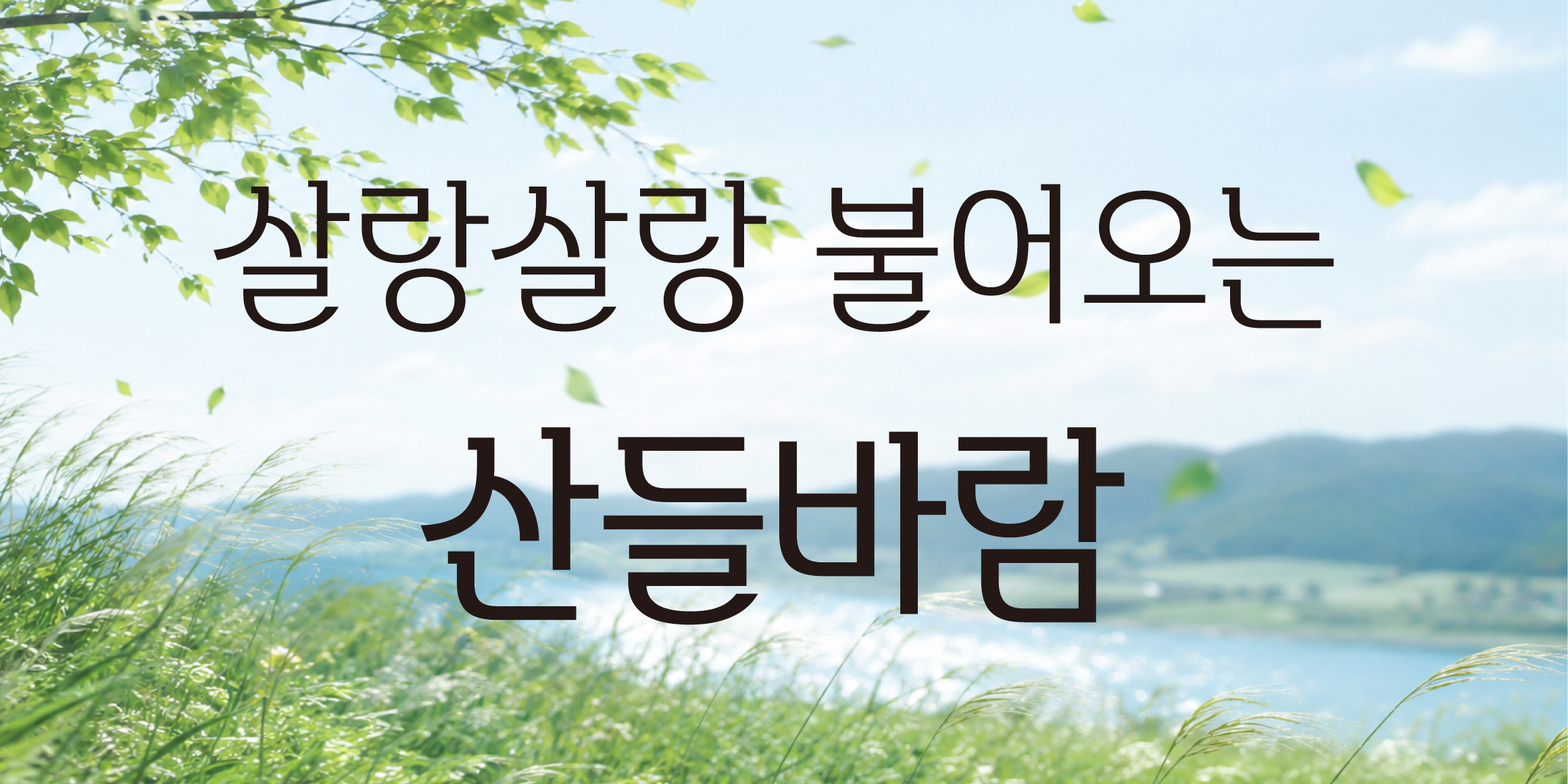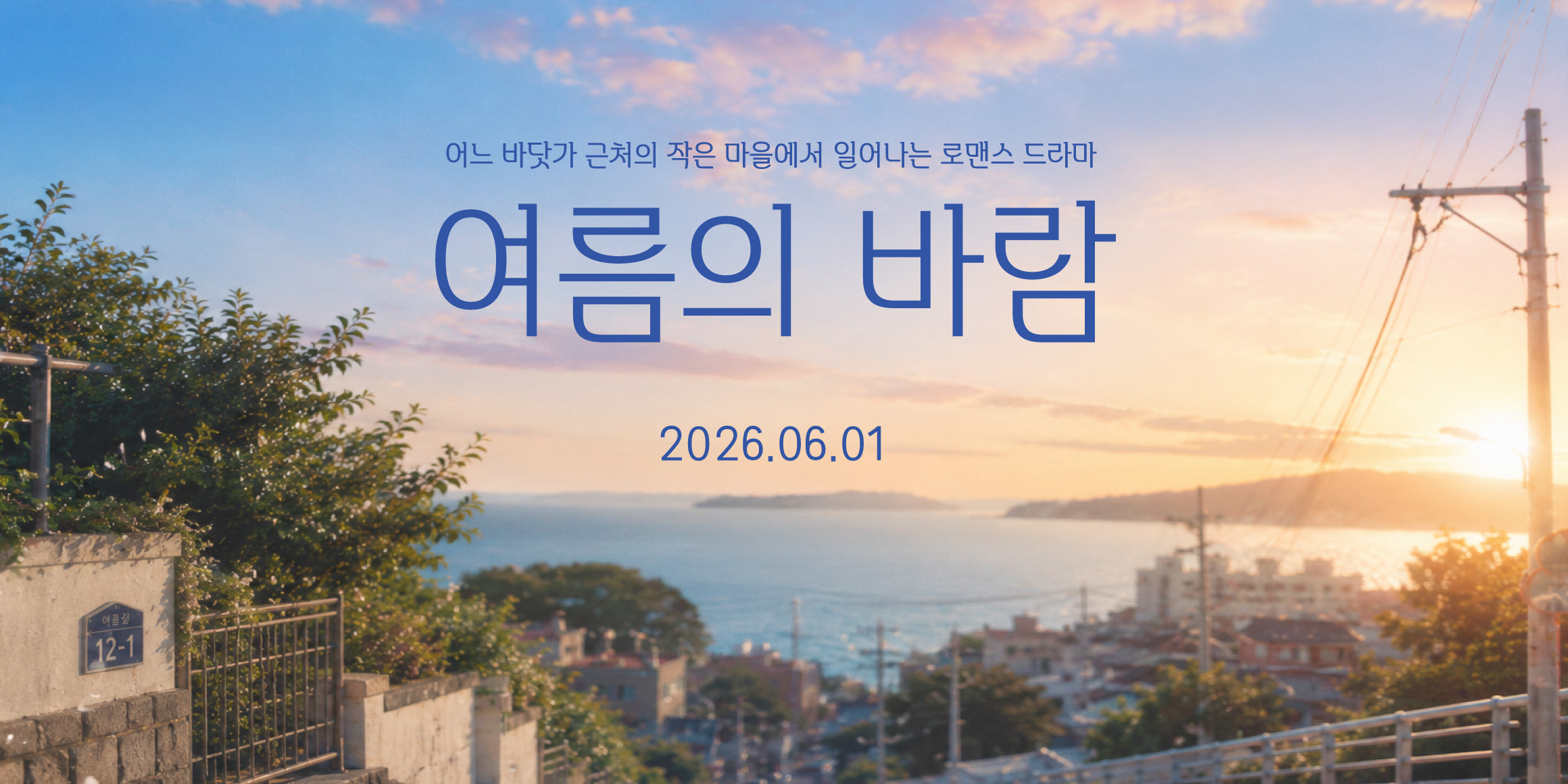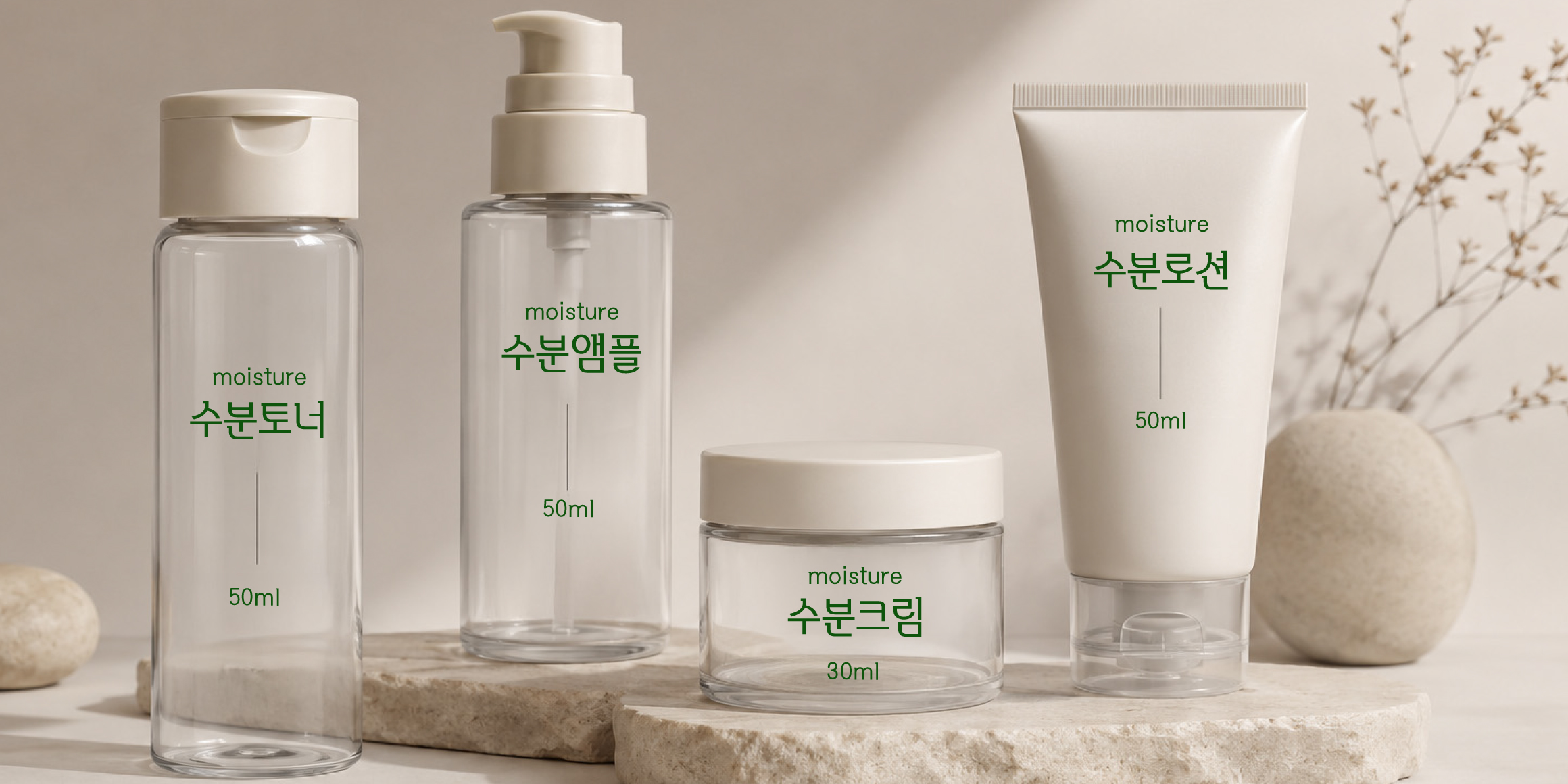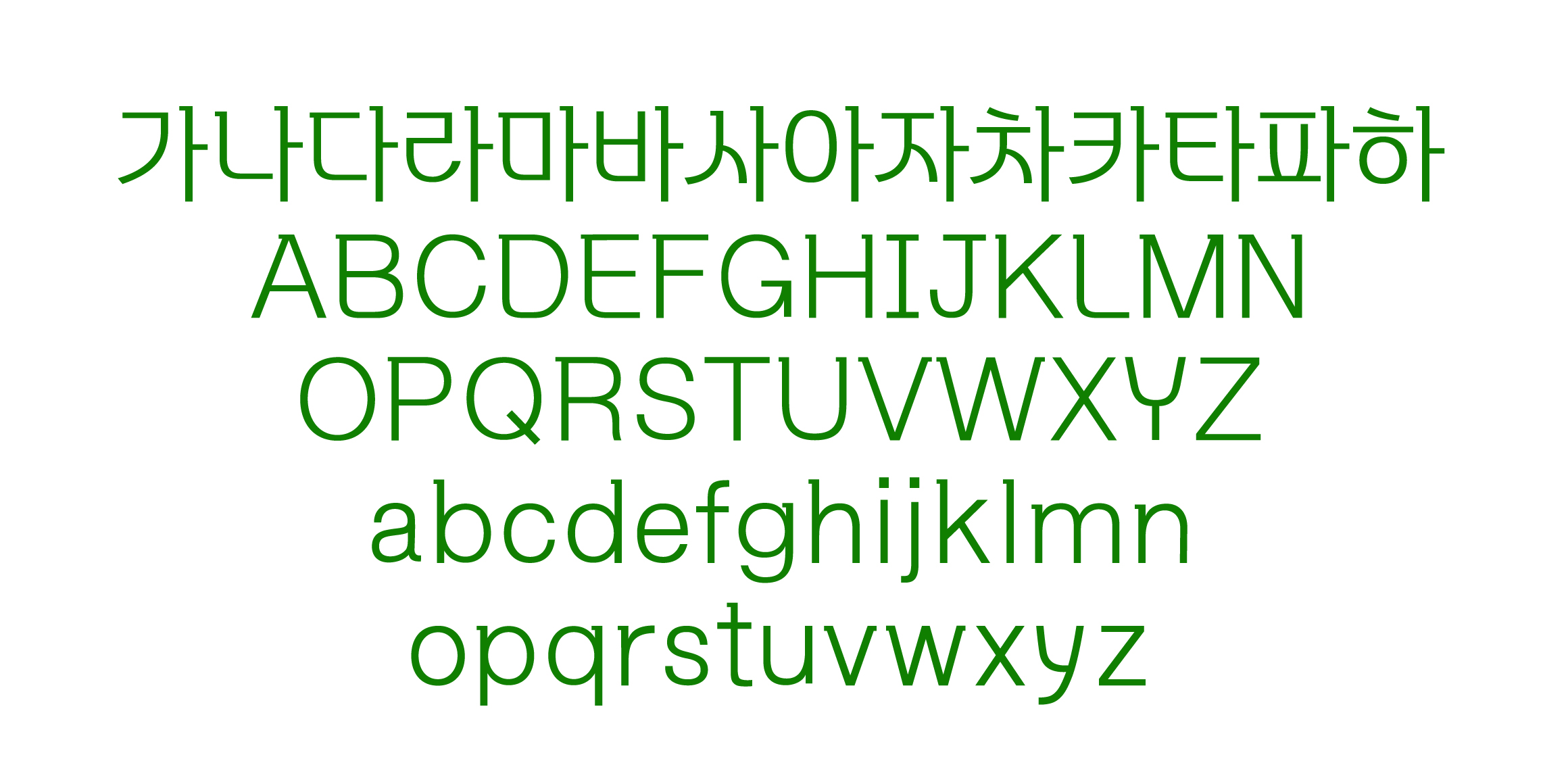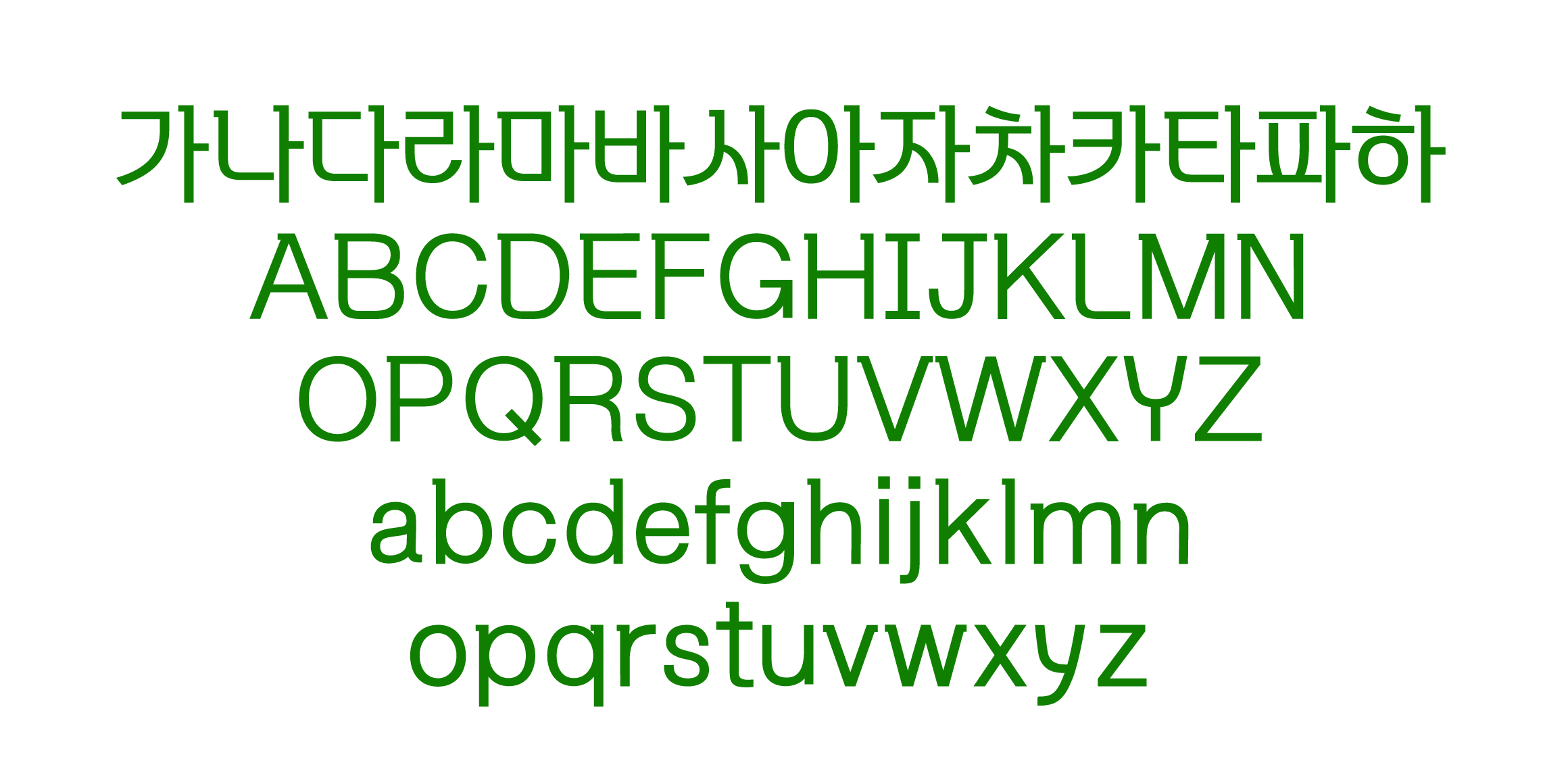
획과 획 사이의 여백을 넓게 확보하여 부드러운 바람이 통하는 듯한 시각적 개방감이 들게 하였다. 자음 “ㅇ,ㅎ”은 완벽한 원형을 유지하되, 내부 공간을 넓혀서 맑고 깨끗한 투명도를 극대화하였고, 단단한 고딕의 골격 위에 모서리나 끝부분을 미세하게 굴려 산들바람의
유연함을 표현했다.
자연 친화적 뷰티 브랜드, 에세이 표지, 라이프스타일 매거진 헤드라인, 모바일 감성 어플리케이션의 본문 및 UI 서체로 사용을 권장한다